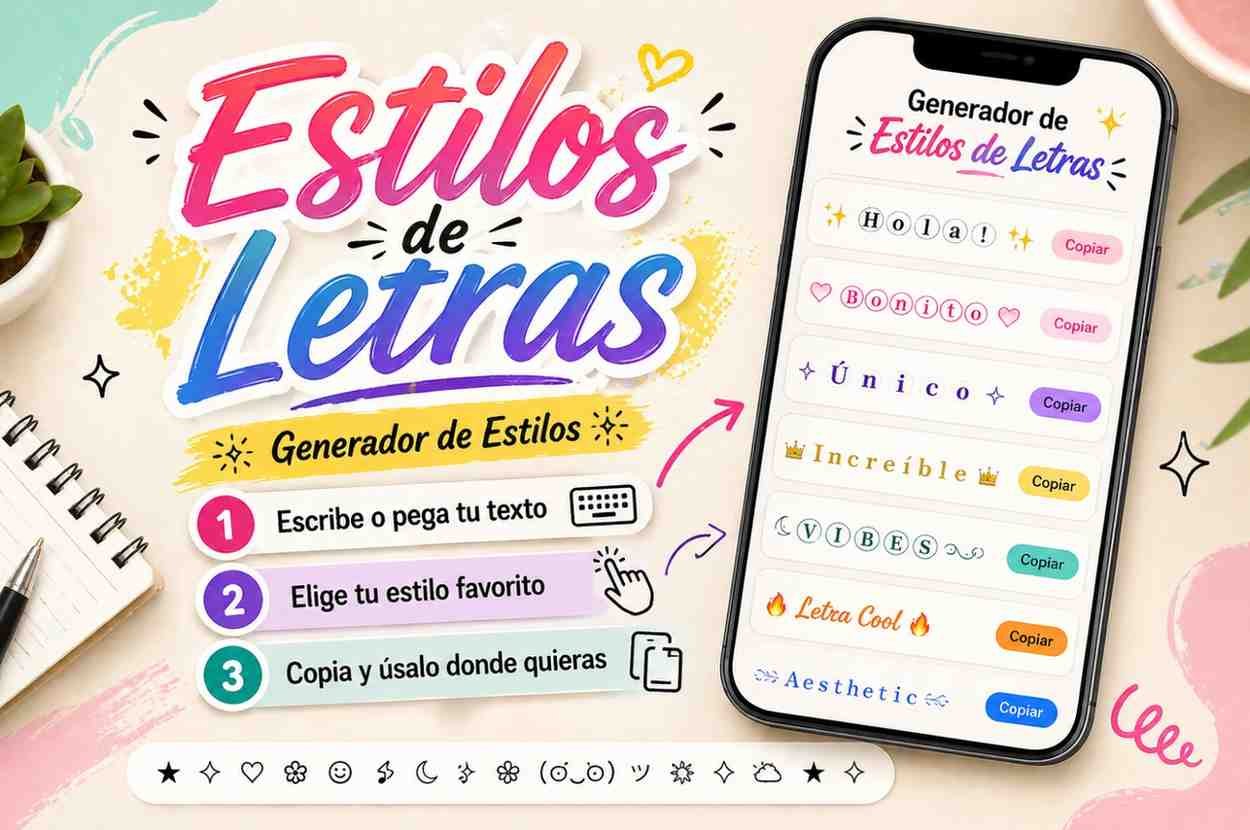
Estilos de Letras ➜ ꧁Copiar y Pegar꧂
Transforma tu texto ordinario en estilos de letras increíbles que harán que tu perfil destaque en
cualquier red social. Con estilos de letras podrás crear nombres decorados, letras bonitas y textos
aesthetic que reflejen tu personalidad. Solo escribe, copia y pega en tu bio, comentarios o
mensajes.
Qué son Estilos de Letras
Los estilos de letras son variaciones decorativas del texto normal que se muestran gracias a caracteres
especiales de Unicode. No se trata de instalar una fuente en el móvil o en el ordenador, sino de copiar
y pegar cadenas de texto ya formateadas que se ven como símbolos, cursivas suaves o formas más
llamativas. Estos formatos funcionan en casi todas las redes sociales y apps de mensajería sin necesidad
de plugins ni ajustes adicionales.
Ejemplos prácticos de estilos de letras
Aquí te dejamos algunos ejemplos de cómo se vería tu nombre "Ana" en diferentes estilos:
𝓔𝓼𝓽𝓲𝓵𝓸𝓼 𝓭𝓮 𝓛𝓮𝓽𝓻𝓪𝓼 — Estilo Cursivo
𝐄𝐬𝐭𝐢𝐥𝐨𝐬 𝐝𝐞 𝐋𝐞𝐭𝐫𝐚𝐬 — Estilo Negrita
𝔈𝔰𝔱𝔦𝔩𝔬𝔰 𝔡𝔢 𝔏𝔢𝔱𝔯𝔞𝔰 — Estilo Gótico
𝕰𝖘𝖙𝖎𝖑𝖔𝖘 𝖉𝖊 𝕷𝖊𝖙𝖗𝖆𝖘 — Estilo Letra Negra
ᴇꜱᴛɪʟᴏꜱ ᴅᴇ ʟᴇᴛʀᴀꜱ — Estilo Pequeño
Estilos de Letras — Estilo Ancho
꧁༒☬ Estilos de Letras ☬༒꧂ — Estilo Gaming
★彡 Estilos de Letras 彡★ — Estilo Estrella
Ⓔⓢⓣⓘⓛⓞⓢ ⓓⓔ Ⓛⓔⓣⓡⓐⓢ — Estilo Circulado
E̷s̷t̷i̷l̷o̷s̷ d̷e̷ L̷e̷t̷r̷a̷s̷ — Estilo Tachado
𝙀𝙨𝙩𝙞𝙡𝙤𝙨 𝙙𝙚 𝙇𝙚𝙩𝙧𝙖𝙨 — Estilo Negrita Cursiva
░E░s░t░i░l░o░s░ ░d░e░ ░L░e░t░r░a░s░ — Estilo Decorado